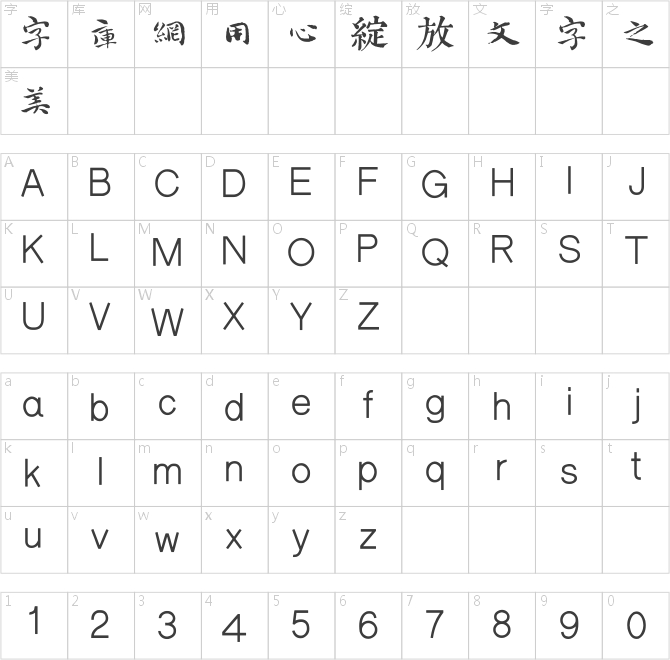
字體名稱: 邯鄲祝允明千字
邯鄲祝允明千字文
邯鄲祝允明千字文字體下載邯鄲(明)祝允明千字文
祝允明(1461年1月17日-1527年1月28日)生于天順四年十二月六日,卒于嘉靖五年十二月二十七日,字希哲,長洲(今江蘇吳縣)人,因長像奇特,而自嘲丑陋,又因右手有枝生手指,故自號枝山,世人稱為“祝京兆”,明代著名書法家。 祝允明的科舉仕途頗為坎坷,十九歲中秀才,五次參加鄉(xiāng)試,才于明弘治五年(1492)中舉,后七次參加會試不第。甚至其子祝續(xù)也在前一科中進士,于是祝允明絕了科舉念頭,以舉人選官,在正德九年(1514),授為廣東興寧縣知縣,嘉靖元年(1522),轉(zhuǎn)任為應天(今南京)府通判,不久稱病還鄉(xiāng)。 祝允明擅詩文,尤工書法,名動海內(nèi)。他與唐寅、文徵明、徐禎卿并稱“吳中四才子”。又與文徵明、王寵同為明中期書家之代表。楷書早年精謹,師法趙孟頫、褚遂良,并從歐、虞而直追“二王”。草書師法李邕、黃庭堅、米芾,功力深厚,晚年尤重變化,風骨爛熳。北京大學教授、引碑入草開創(chuàng)者的李志敏評價:“祝枝山的狂草,骨力弱于旭、素,但在宋人影響下,又自成一格”。  其代表作有《太湖詩卷》《箜篌引》《赤壁賦》等。所書“六體書詩賦卷”“草書杜甫詩卷”“古詩十九首”“草書唐人詩卷”及“草書詩翰卷”等皆為傳世墨寶。